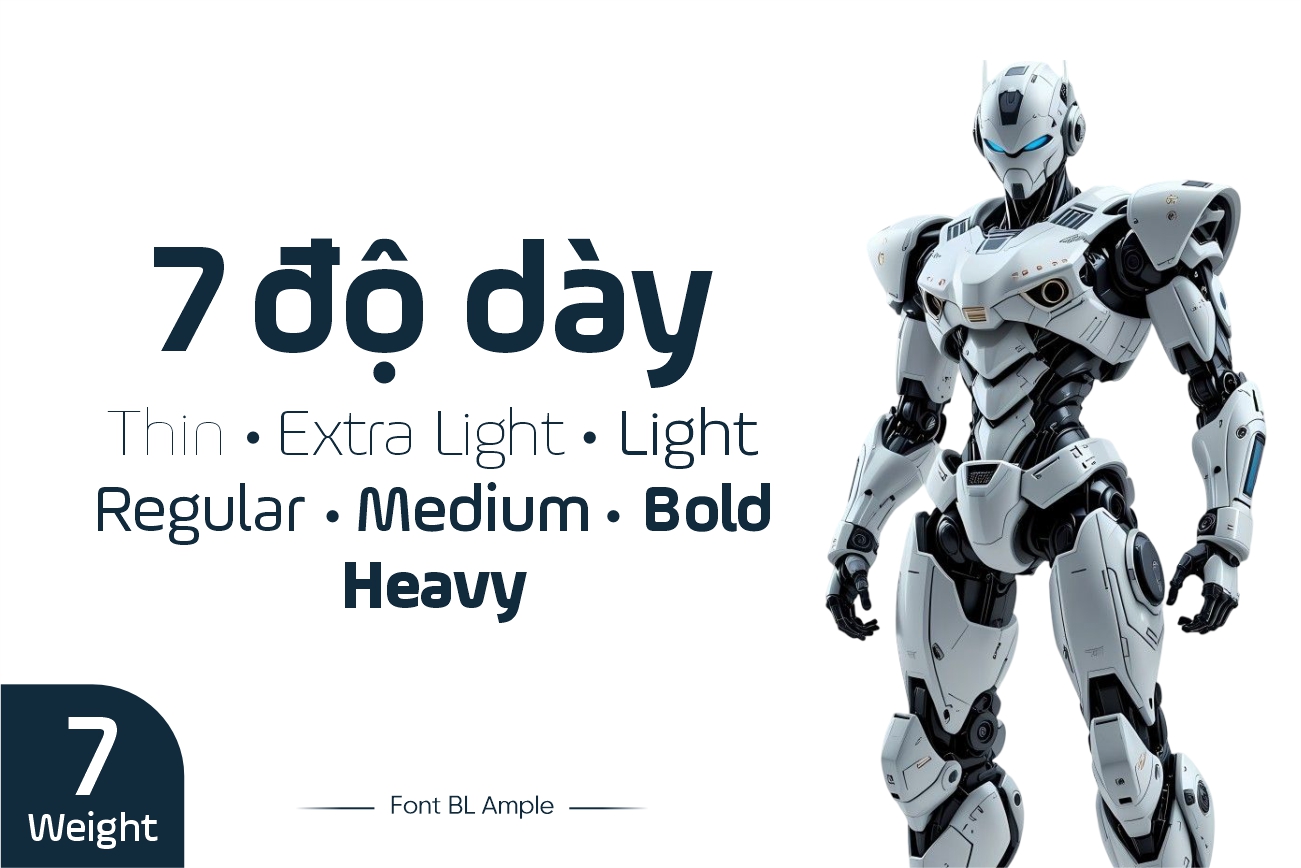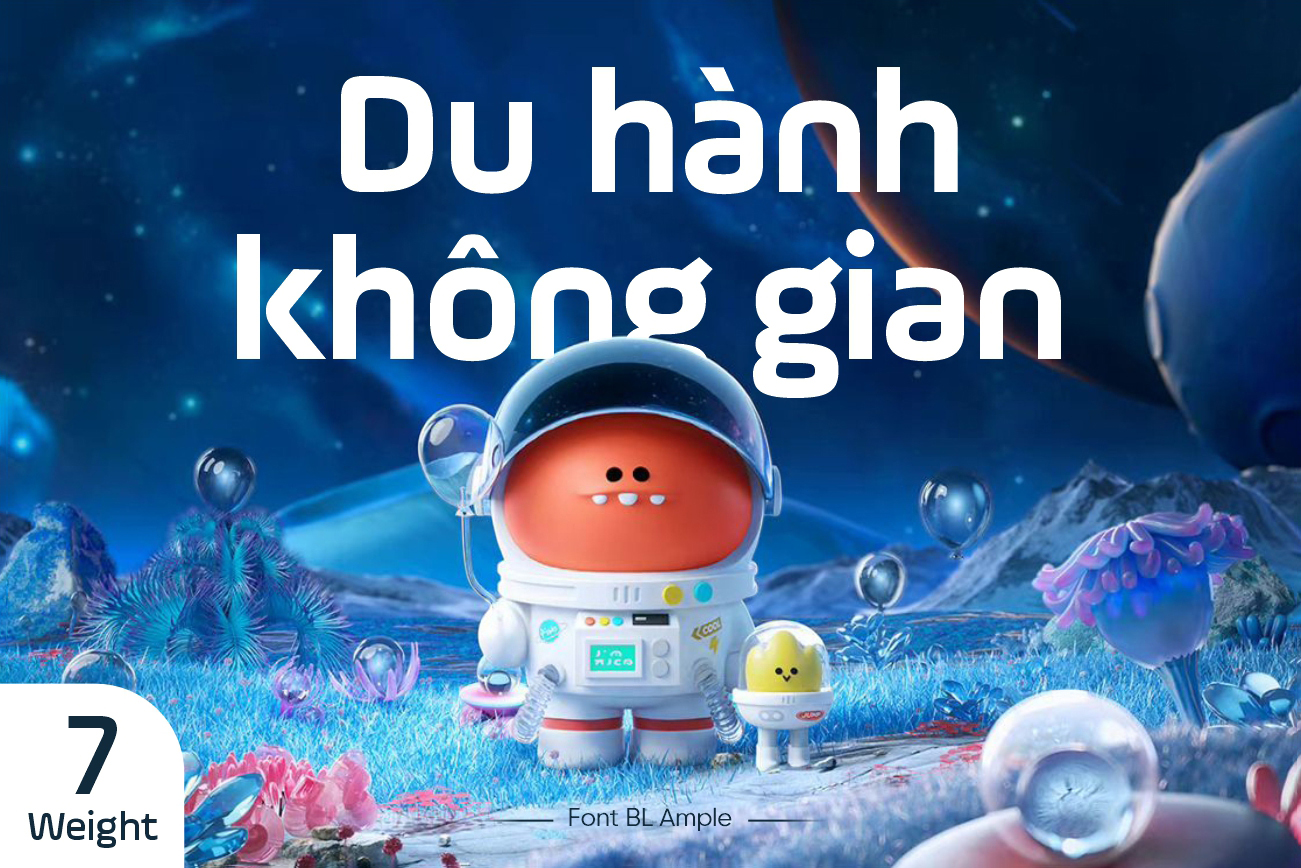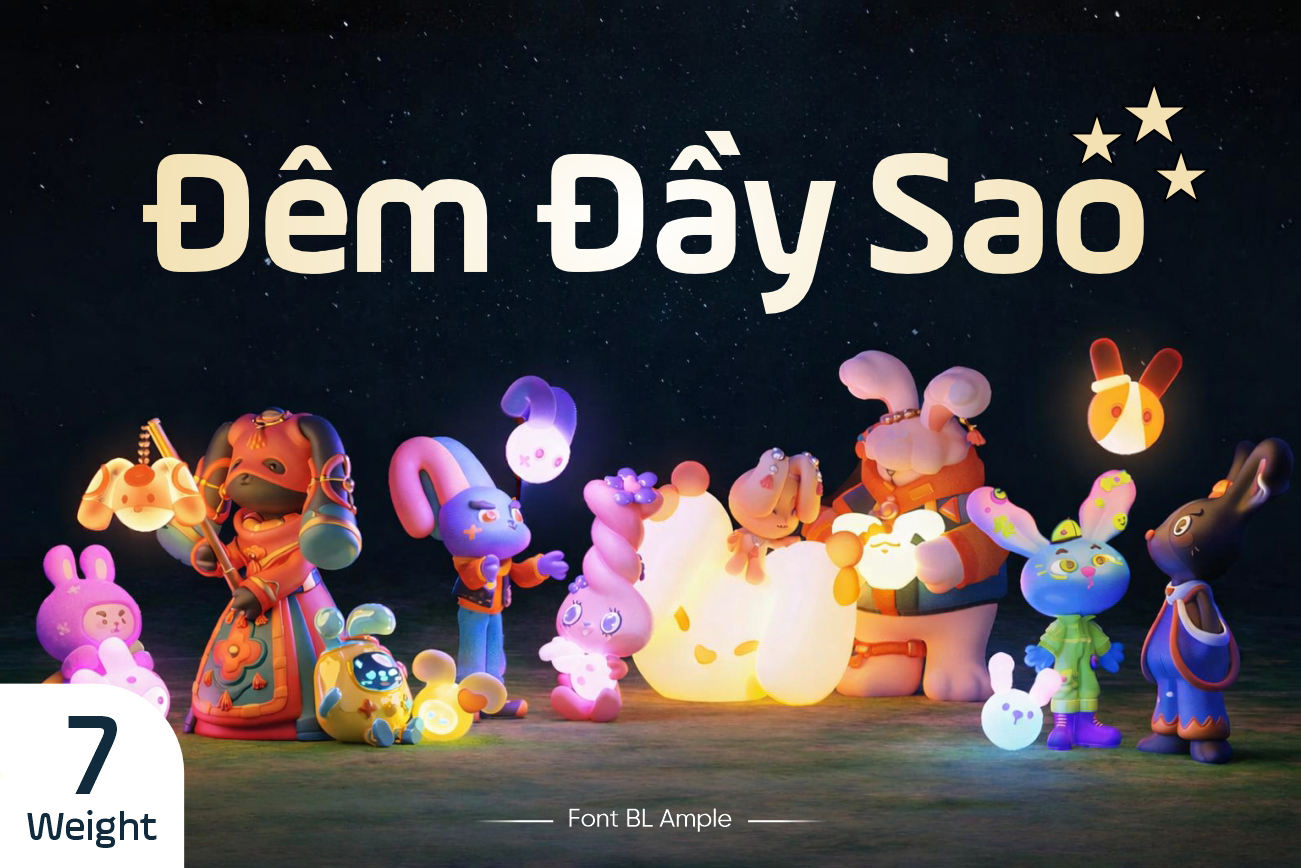
Bộ font BL Ample - Font chữ công nghệ mạnh mẽ và thu hút
BL Ample là phiên bản Việt hóa của font chữ Ample do Aakash Soneri thiết kế, được Team BL chỉnh sửa và hoàn thiện để sử dụng trọn vẹn trong môi trường tiếng Việt. Ample ngay từ đầu đã được định hướng là một kiểu chữ hiện đại, phục vụ cho các nhu cầu thiết kế số, giao diện và truyền thông thương hiệu. Sau quá trình Việt hóa, BL Ample không chỉ giữ nguyên tinh thần thiết kế ban đầu mà còn được tối ưu về dấu, khoảng cách và tỷ lệ ký tự, giúp người dùng dễ dàng ứng dụng trong các dự án thực tế mà vẫn đảm bảo tính thẩm mỹ và độ chính xác cao.
Về kiểu dáng, BL Ample mang đặc trưng rõ rệt của font chữ công nghệ, với cấu trúc chữ gọn gàng, hình học và dứt khoát. Các nét chữ có độ đều cao, trục thẳng rõ ràng, tạo cảm giác chắc chắn và hiện đại. Nhờ cách xử lý hình khối thông minh, font vừa thể hiện được sự mạnh mẽ, bắt mắt và thu hút, vừa giữ được độ dễ đọc cần thiết khi sử dụng ở kích thước nhỏ hoặc trong bố cục nhiều chữ. Tổng thể kiểu chữ mang tinh thần trung tính, phù hợp với nhiều phong cách thiết kế từ tối giản đến đậm chất công nghệ.
BL Ample đặc biệt phát huy hiệu quả trong các thiết kế liên quan đến thương hiệu, sản phẩm số và truyền thông hiện đại. Khi sử dụng cho tiêu đề, font tạo ấn tượng thị giác rõ ràng, giúp nội dung trở nên nổi bật và chuyên nghiệp hơn. Trong các ấn phẩm như website, ứng dụng, poster công nghệ hay banner quảng cáo, BL Ample thể hiện đúng tinh thần của một font chữ công nghệ: rõ ràng, hiện đại và có tính hệ thống cao. Sự mạnh mẽ, bắt mắt và thu hút của font giúp thông điệp được truyền tải nhanh chóng, phù hợp với nhịp độ tiếp nhận thông tin của người dùng hiện nay.
Xét về nguồn gốc, Ample là kết quả của tư duy thiết kế chú trọng vào tính ứng dụng lâu dài và khả năng thích nghi đa nền tảng của Aakash Soneri. Thông qua quá trình Việt hóa, Team BL đã tinh chỉnh từng chi tiết nhỏ để BL Ample hoạt động ổn định với tiếng Việt, đồng thời giữ trọn tinh thần thiết kế nguyên bản. Nhờ đó, BL Ample trở thành lựa chọn đáng tin cậy cho các nhà thiết kế đang tìm kiếm một font chữ hiện đại, mang hơi hướng công nghệ, vừa mạnh mẽ vừa linh hoạt, đáp ứng tốt nhu cầu sử dụng trong các dự án sáng tạo và thương mại chuyên nghiệp.